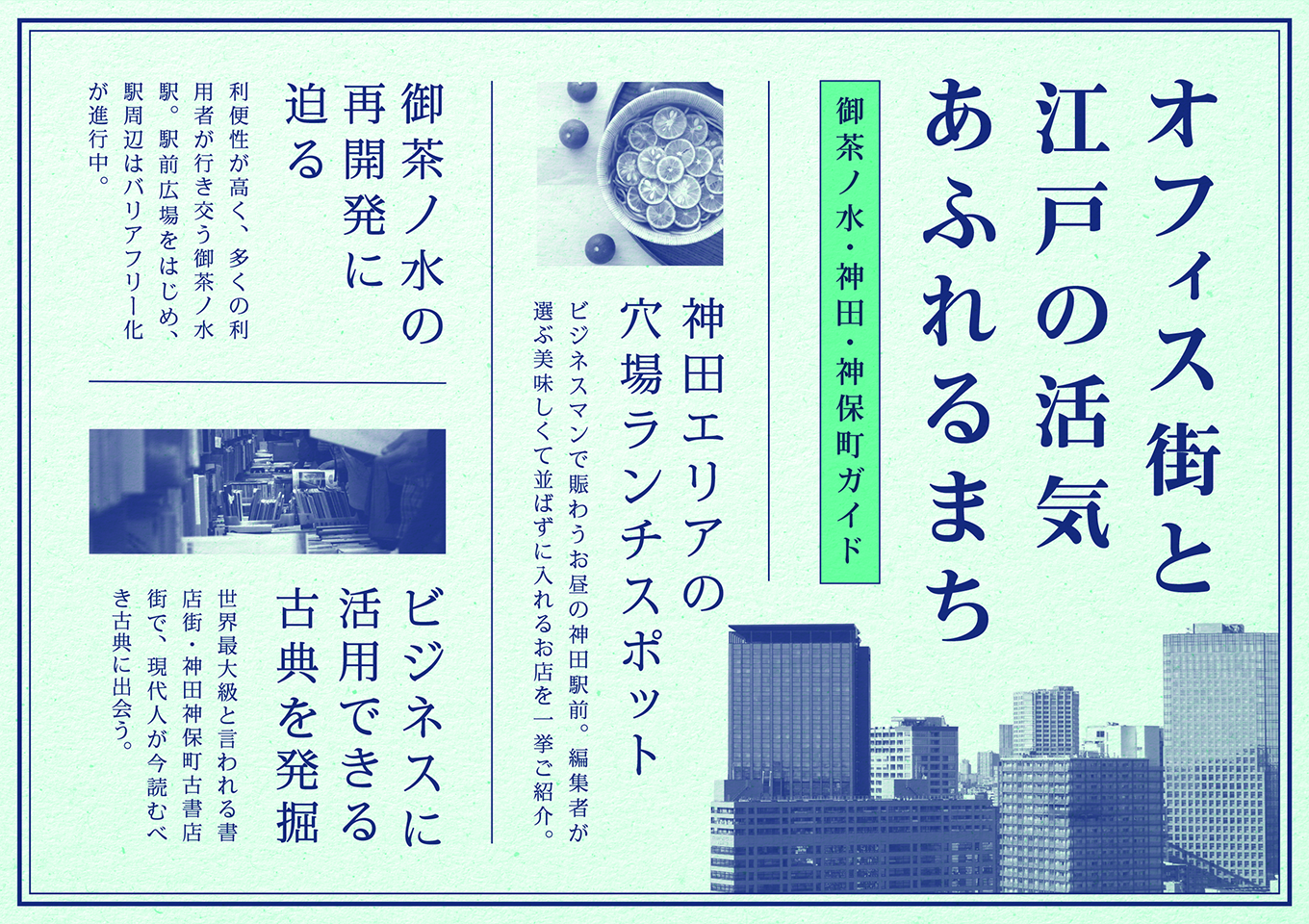
毎日新聞社が開発した、モダンテイストの明朝体です。新聞紙面の見出しとして使われている書体をベースにしており、正体利用を想定したデザインです。コントラストが低く、横画やハライの先端も太めに処理しており、視認性が高いデザインになっています。M/B/Hの3ウエイトはそれぞれ個別にデザインされていて、ウエイト間で微細なニュアンスの違いを演出します。